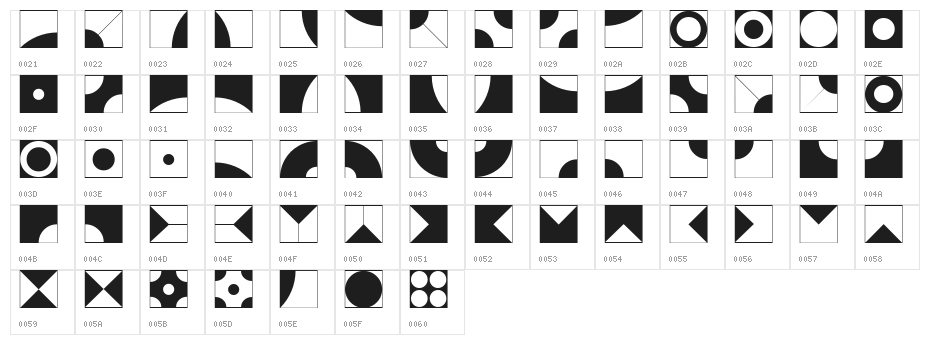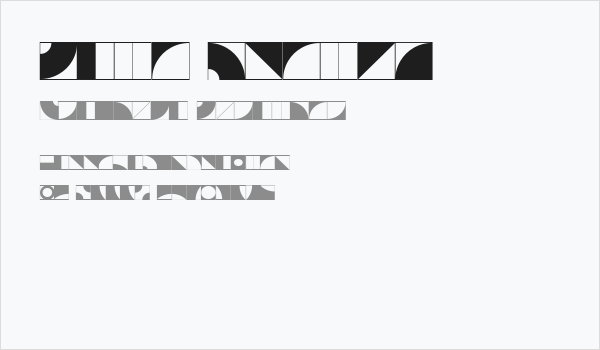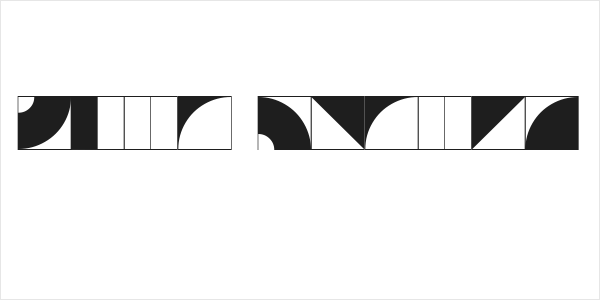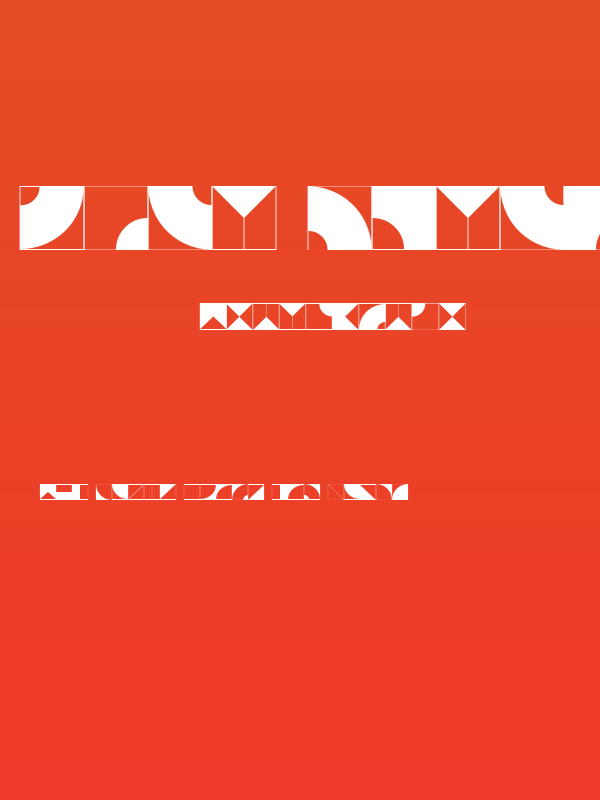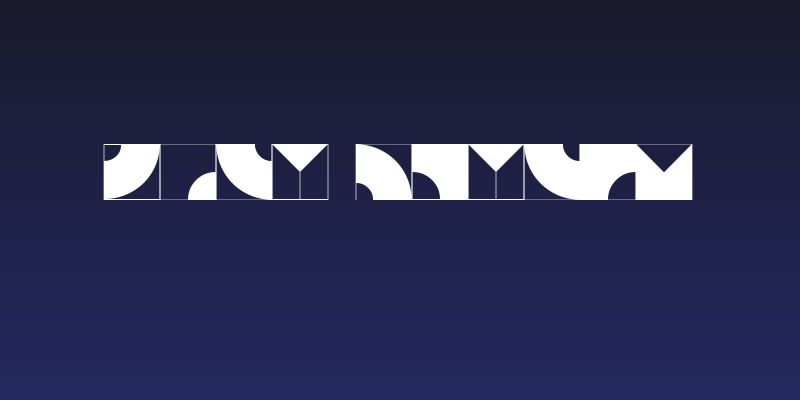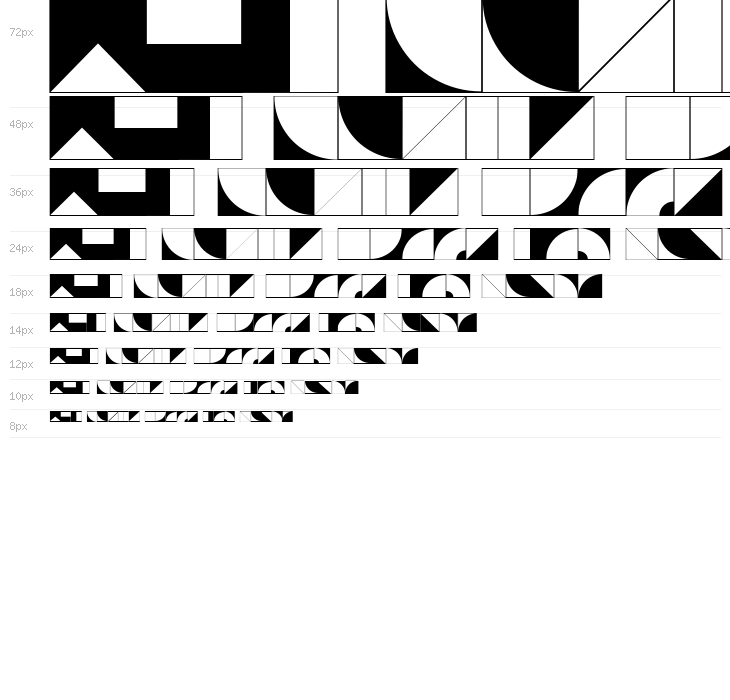
Deco Blocks Font
| Categorías | Art Deco |
| Caso de uso | Decorative art, Graphic design, Architectural elements |
| Proyectos propuestos | Ideal for architectural motifs, interior design elements, graphic design projects, and decorative art installations. |